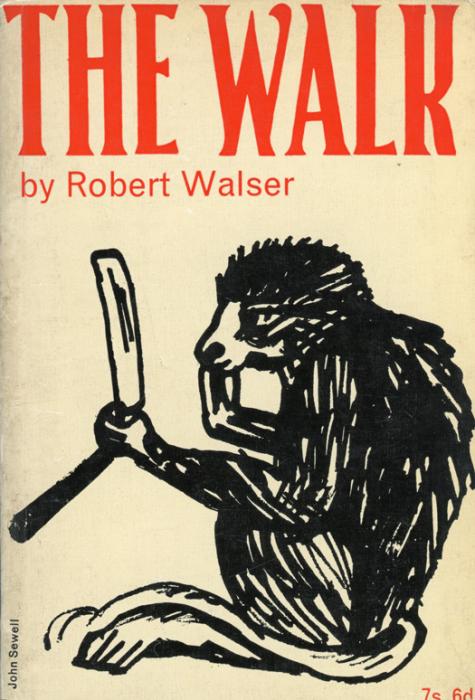
Schrift von Buchcover "The Walk"
Das ist von Hand illustriert. Jede Serife ist anders …
... aber schön ist es doch. Ich hab ein (nostalgisches?) Faible für solche klaren Cover, seufz ... (hab im Weihnachtstrubel wohl gerade zu viele weiße/schwarze Thriller-Cover mit extrem vielen "Distortions" und roten, spotlackierten, blutenden Buchstaben gesehen).
... aber schön ist es doch.
Ja, das finde ich auch. Der Hinweis war auch nicht negativ gemeint, sondern sollte nur als Erkennungsmerkmal dafür gesehen werden, dass höchstwahrscheinlich keine Schriftart verwendet wurde. Solche illustrierten Titel gibt es mittlerweile leider viel zu selten.
... hab's auch nicht negativ verstanden. Hab gerade, inspiriert durch diesen Thread, das hier gefunden:
Mehr Nostalgisches zum Schwelgen. Mir gefällt das, wenn die Beschränkung der Mittel den Fokus auf die Gestaltung leitet. Photoshop ist super, aber manchmal auch mehr Fluch als Segen.